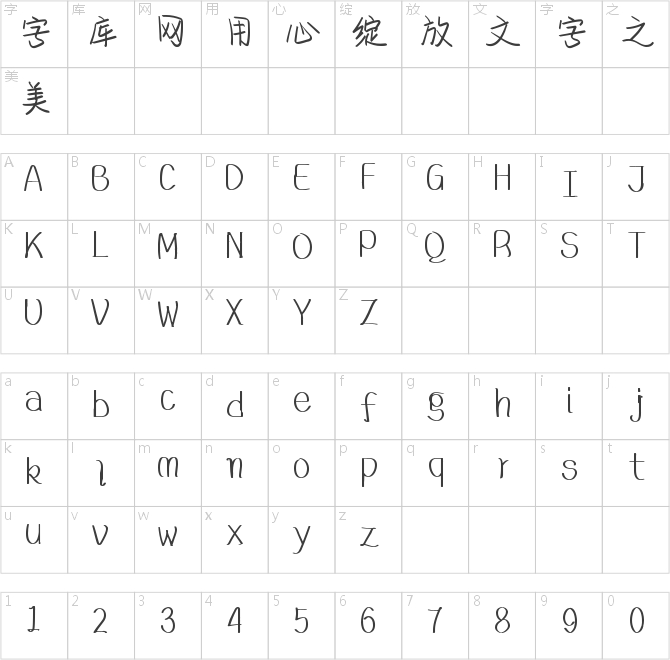
你是藏在微風(fēng)的
你是藏在微風(fēng)的喜歡字體字庫(kù)是一款讓人賞心悅目、百看不厭的中文字體,適合各類(lèi)廣告和產(chǎn)品包裝設(shè)計(jì)應(yīng)用,字體大小3.45MB,格式為ttf字體,上傳用戶(hù)是文道字庫(kù),作者/版權(quán)方為文道字庫(kù)